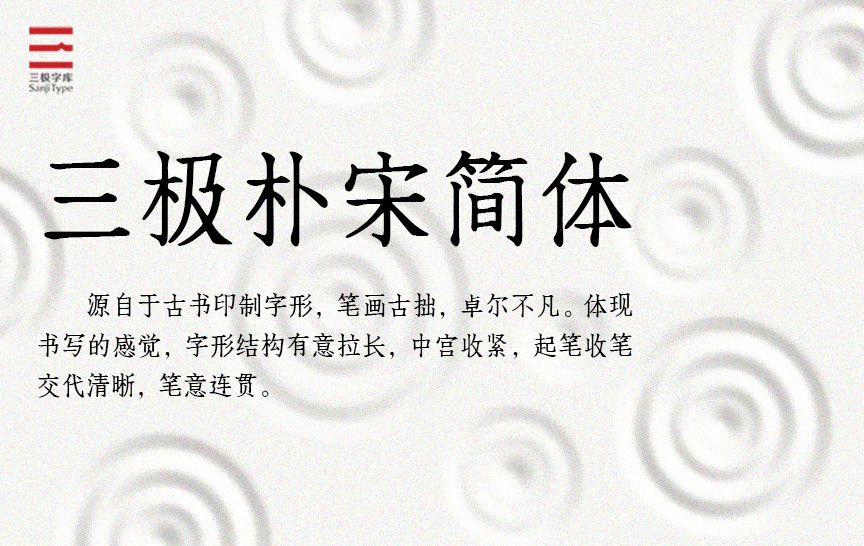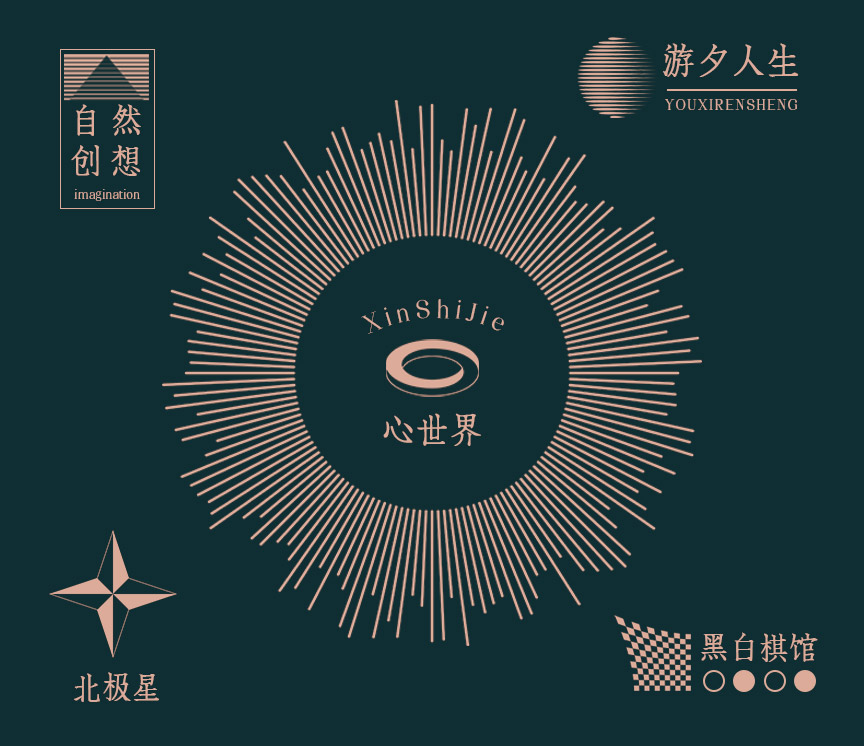
三极朴宋简体
字体名称:三极朴宋简体
设计师:Zhouzhou
所属分类:宋体
三极朴宋简体源自于古书印制字形,笔画古拙,卓尔不凡。体现书写的感觉,字形结构有意拉长,中宫收紧,起笔收笔交代清晰,笔意连贯。适用于古装书排版,包装设计,logo设计等。
适用媒介:杂志、书籍、广告、标志、宣传册、包装、影视、动漫、交互设计。